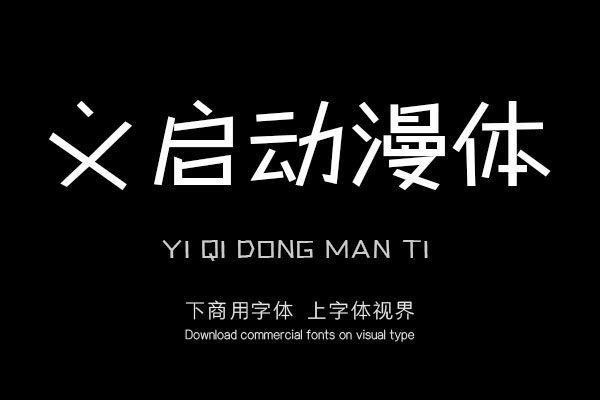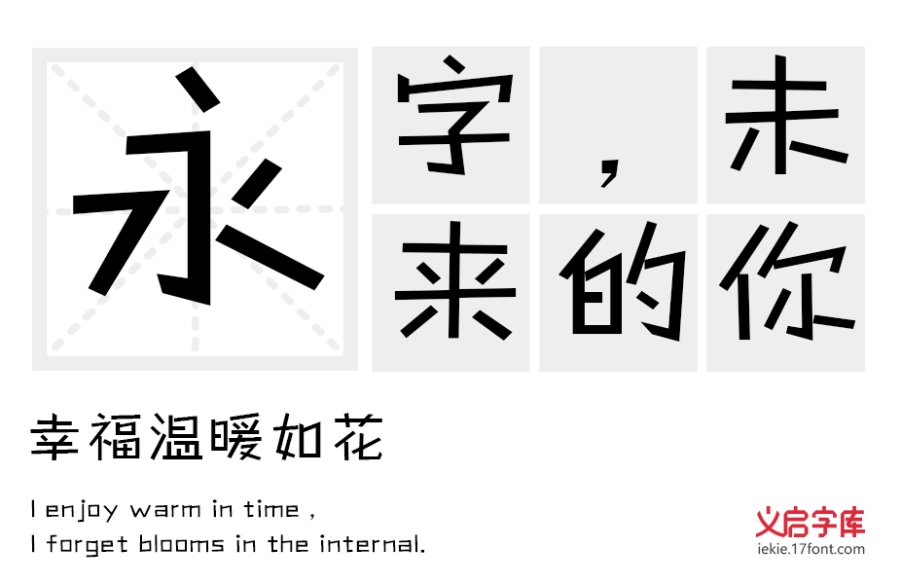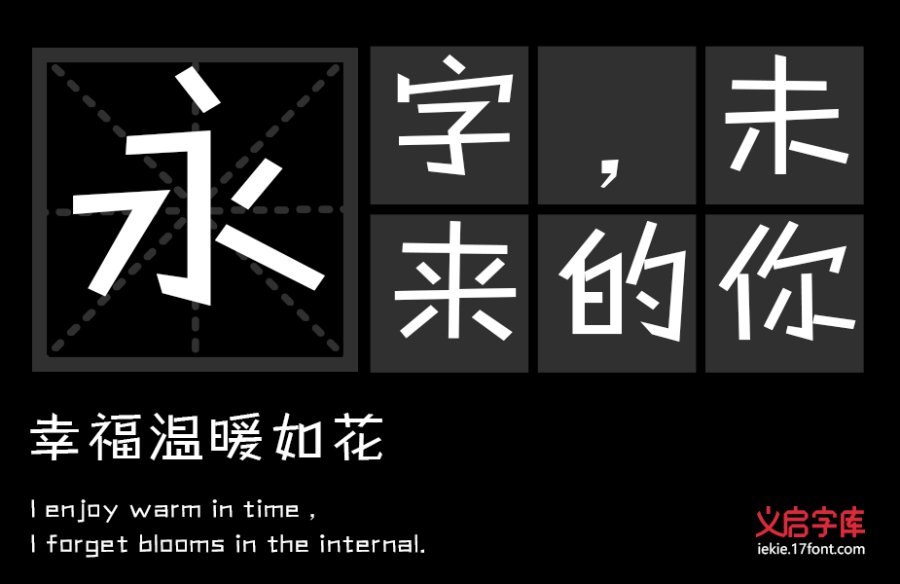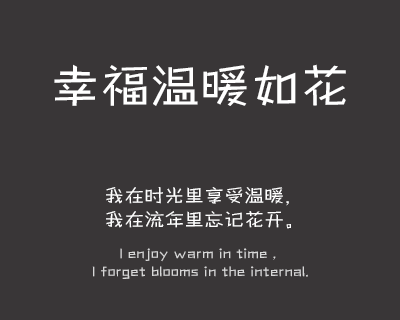
葫芦兄弟,黑猫警长,喜羊羊与灰太狼,龙珠,火影忍者,海贼王,随着时代发展,一部部优秀的动漫作品问世。 “动漫”即“动画”和“漫画”,但义启字库赋予这个名字新的含义,即“动感十足”和“漫不经心”。 义启动漫体,章法律动上更接近手写,左右忽悠感很强,字间距把握考究,整体气息舒畅爽朗。结构上显得动感十足,笔画上看似漫不经心,但各个字实则十分考究,生机勃勃又融为一体,整体一气呵成。分享到